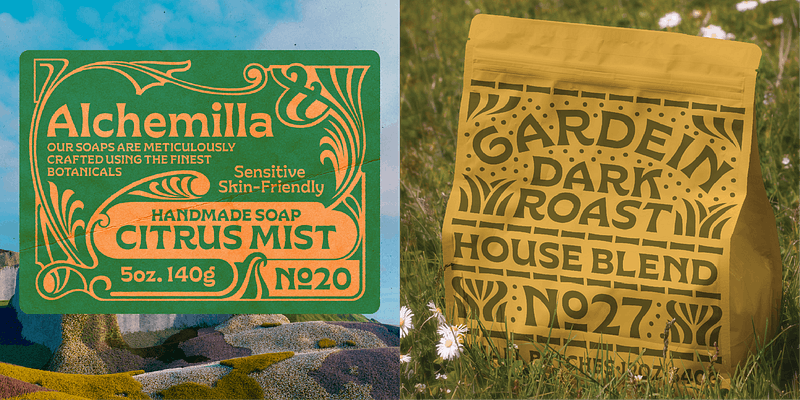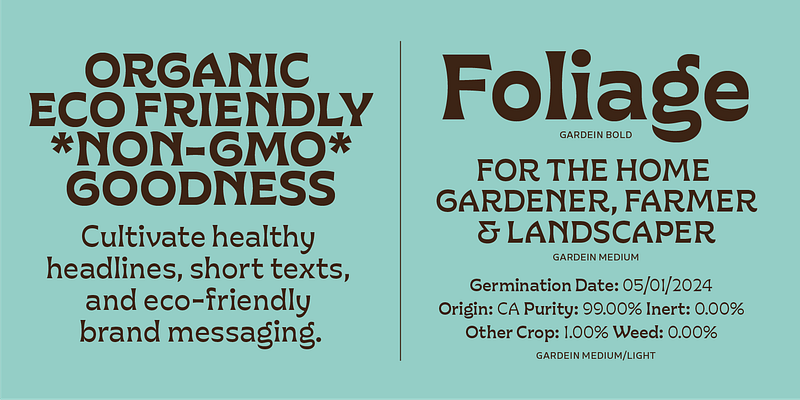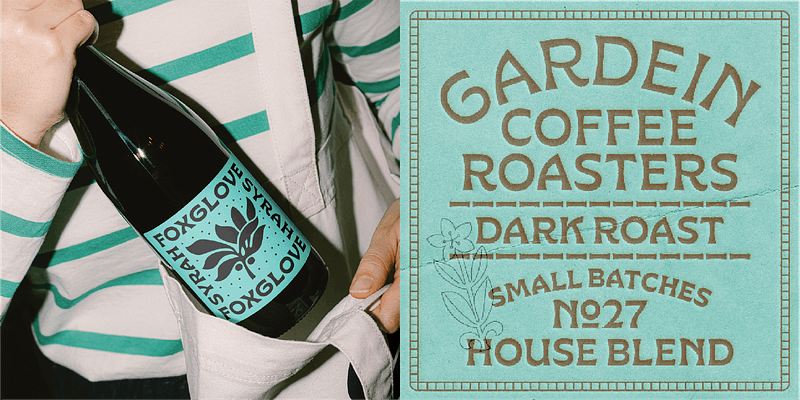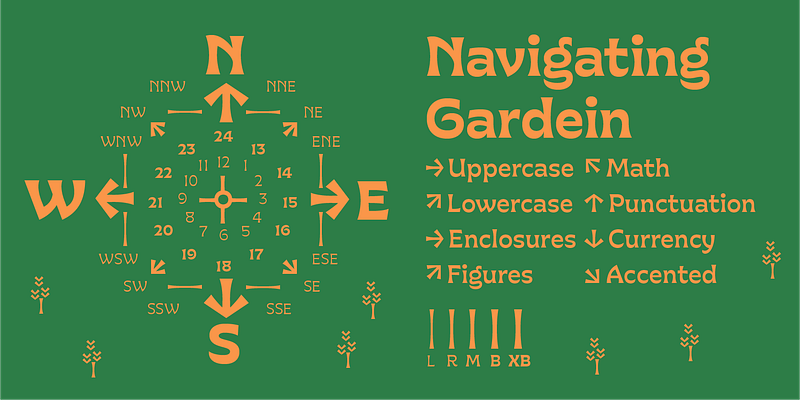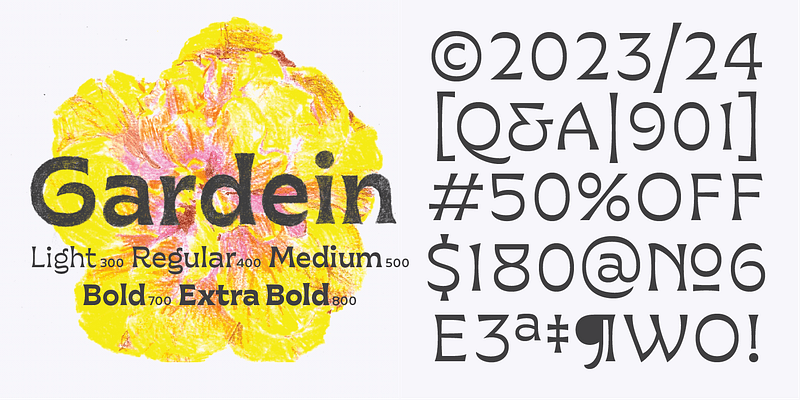
La tipografía Gardein, con toques humanistas poco convencionales, despliegan una textura sorprendente tanto en las páginas como en otros contextos. Desarrollada sobre una base romana, los tallos cóncavos se adornan con terminaciones acampanadas, con grosor adicional a la altura de x y la línea de base, lo que aporta un aroma fresco y orgánico a los títulos, los textos breves y los mensajes de marcas respetuosas con el medioambiente. La familia incluye cinco grosores, de Light a Extra Bold.
Gardein se inspira en la bellísima obra en portadas de libros de Sarah W. Whitman (1842-1904), vitralista, pintora y diseñadora estadounidense cuya estética se vio enormemente influenciada por el movimiento Arts and Crafts.
Gardein se diseñó con Christopher Caldwell © 2024 con Troy Leinster.